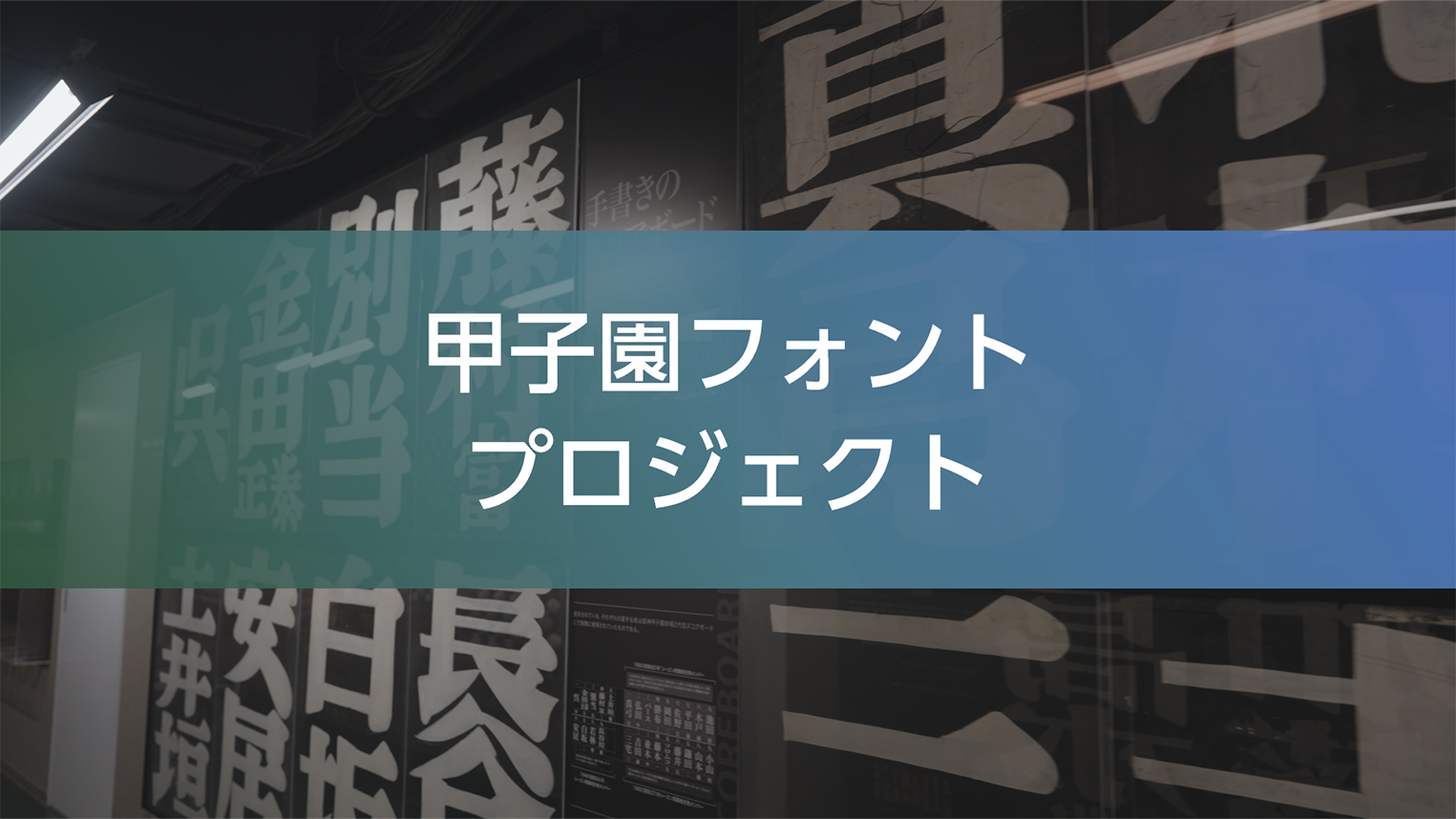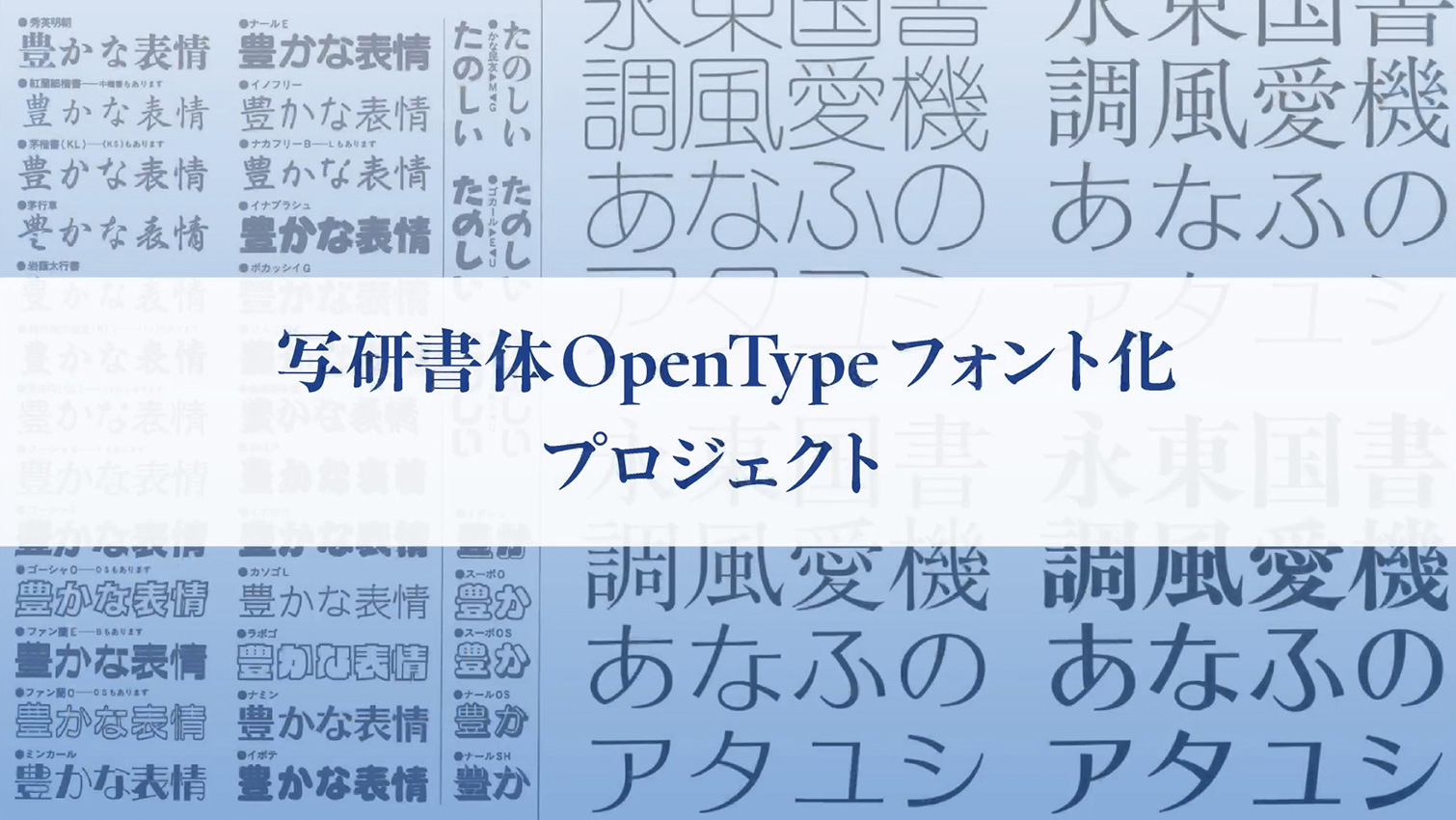
邦文写真植字機
100周年プロジェクト
2024年7月24日に邦文写真植字機発明から100周年となりました。100周年記念に行った「写研書体OpenTypeフォント化プロジェクト」「甲子園フォントプロジェクト」をご紹介します。
写研書体OpenTypeフォント化プロジェクト
DTPの普及とともに写研書体は活躍の機会を減らしたものの、そのデザインの優美さと多様さは、今なお多くのファンを魅了しています。そして、邦文写真植字機発明100周年を迎えたことを機に写研書体のOpenTypeフォント開発プロジェクトを開始し、2024年10月15日に写研フォントの提供を開始しました。
甲子園フォントプロジェクト
邦文写真植字機と時を同じくする阪神甲子園球場も、2024年に開場100周年を迎えました。
阪神甲子園球場とモリサワは、100周年記念共同プロジェクトとして、同球場のスコアボードで使用してきた伝統の「甲子園文字」を受け継ぎ、『甲子園フォント』として制作、デジタルフォント化いたしました。